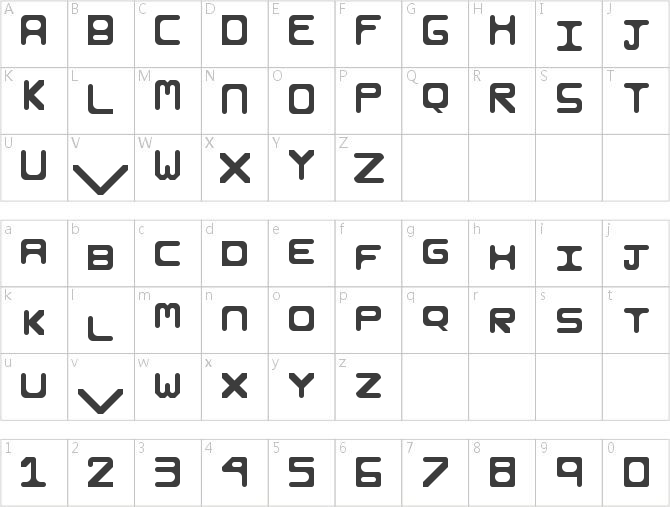
C u d d l e s S p a c e d
C u d d l e s S p a c e d介紹
C u d d l e s S p a c e d字體字庫是一款讓人賞心悅目、百看不厭的英文字體,適合各類廣告和產品包裝設計應用,字體大小0.02MB,格式為ttf字體,上傳用戶是洛洛,作者/版權方為未知
C u d d l e s S p a c e d效果圖